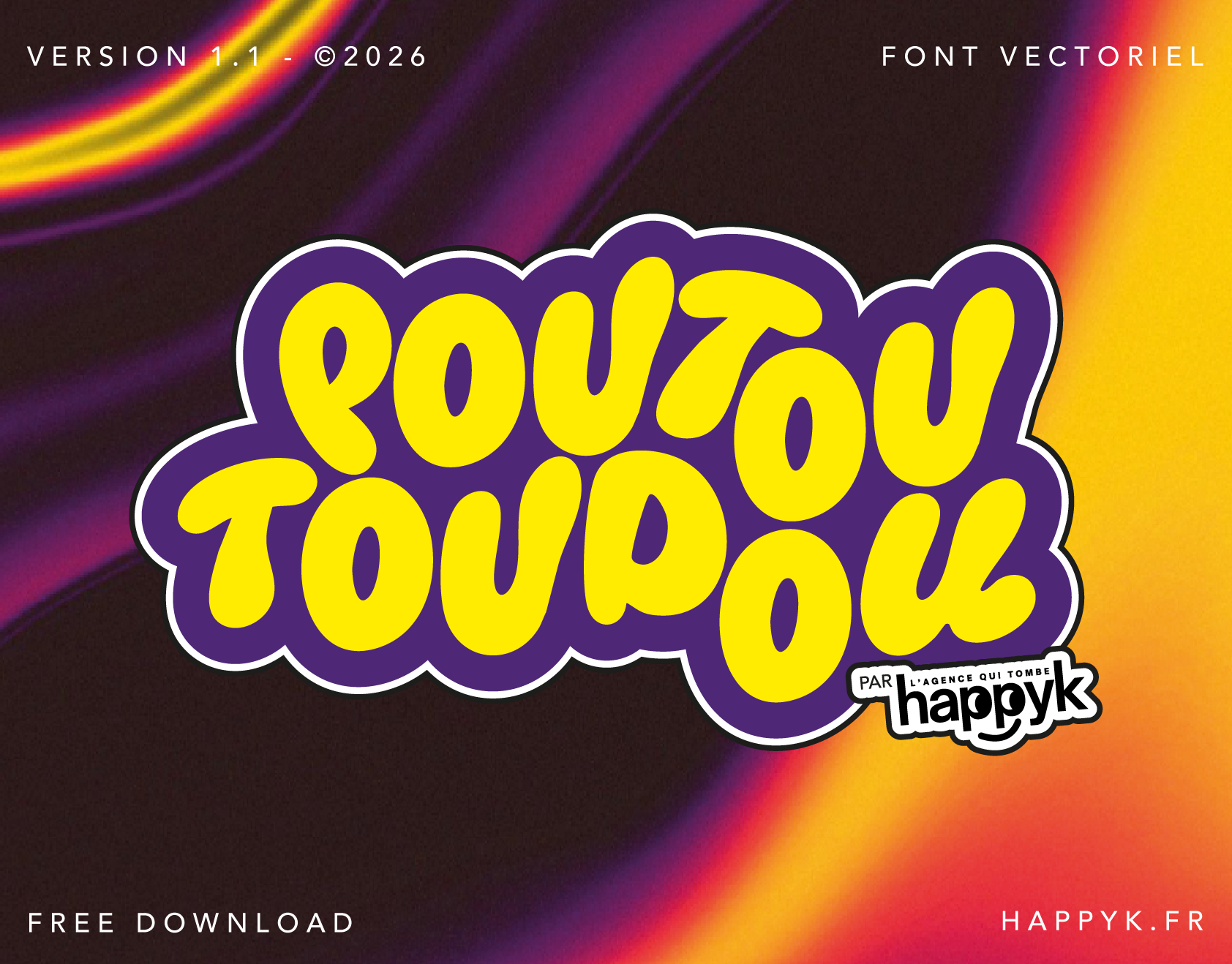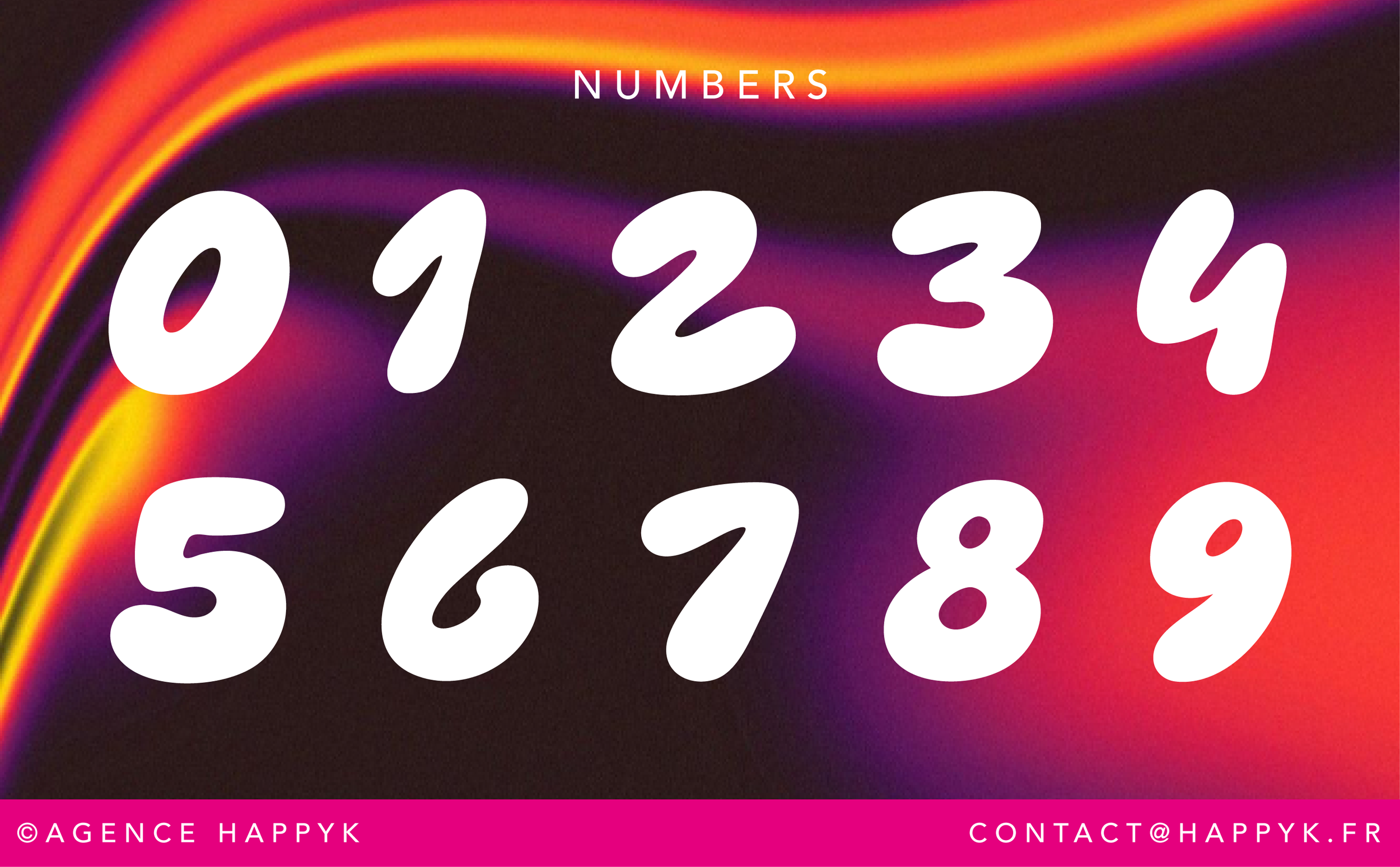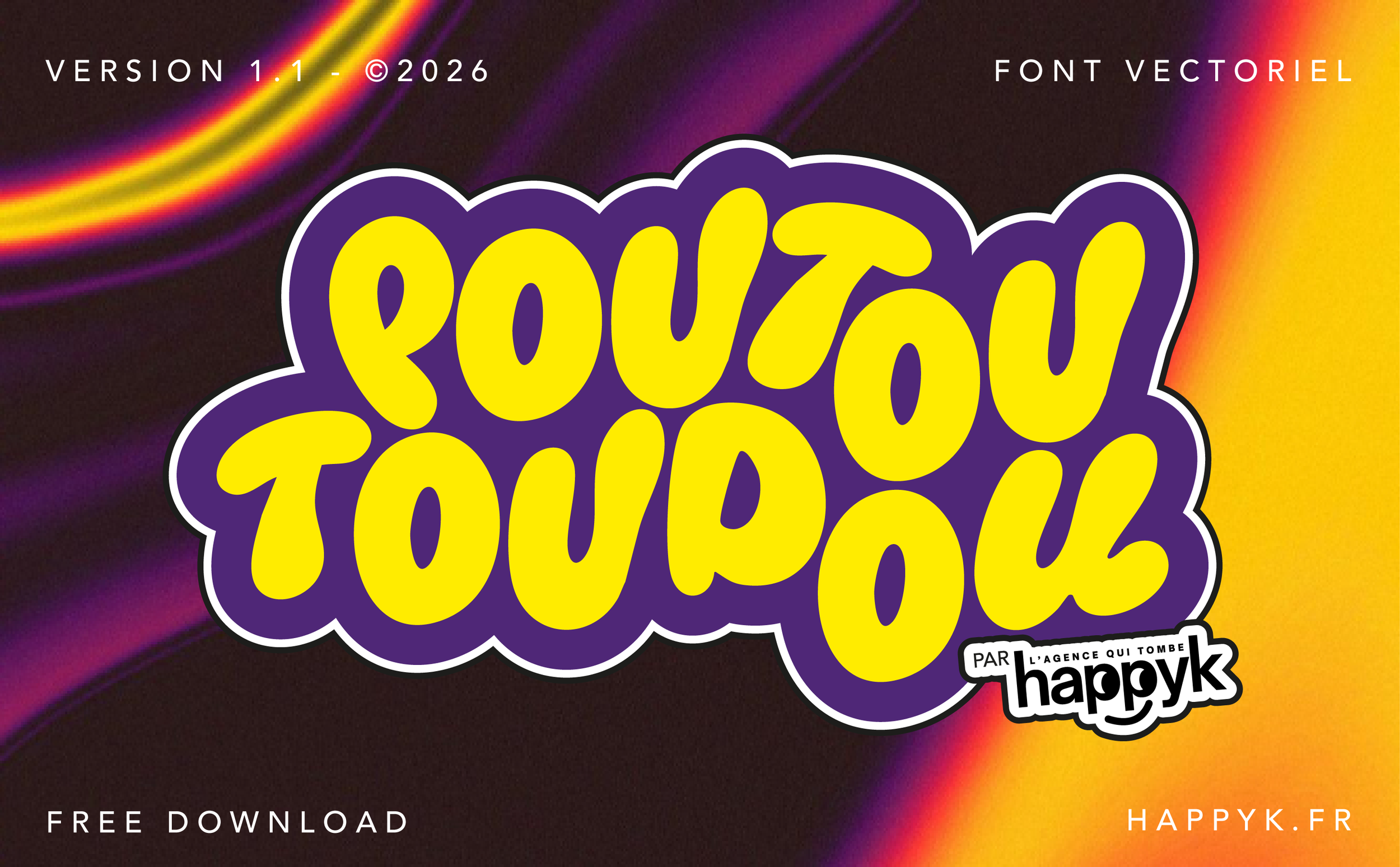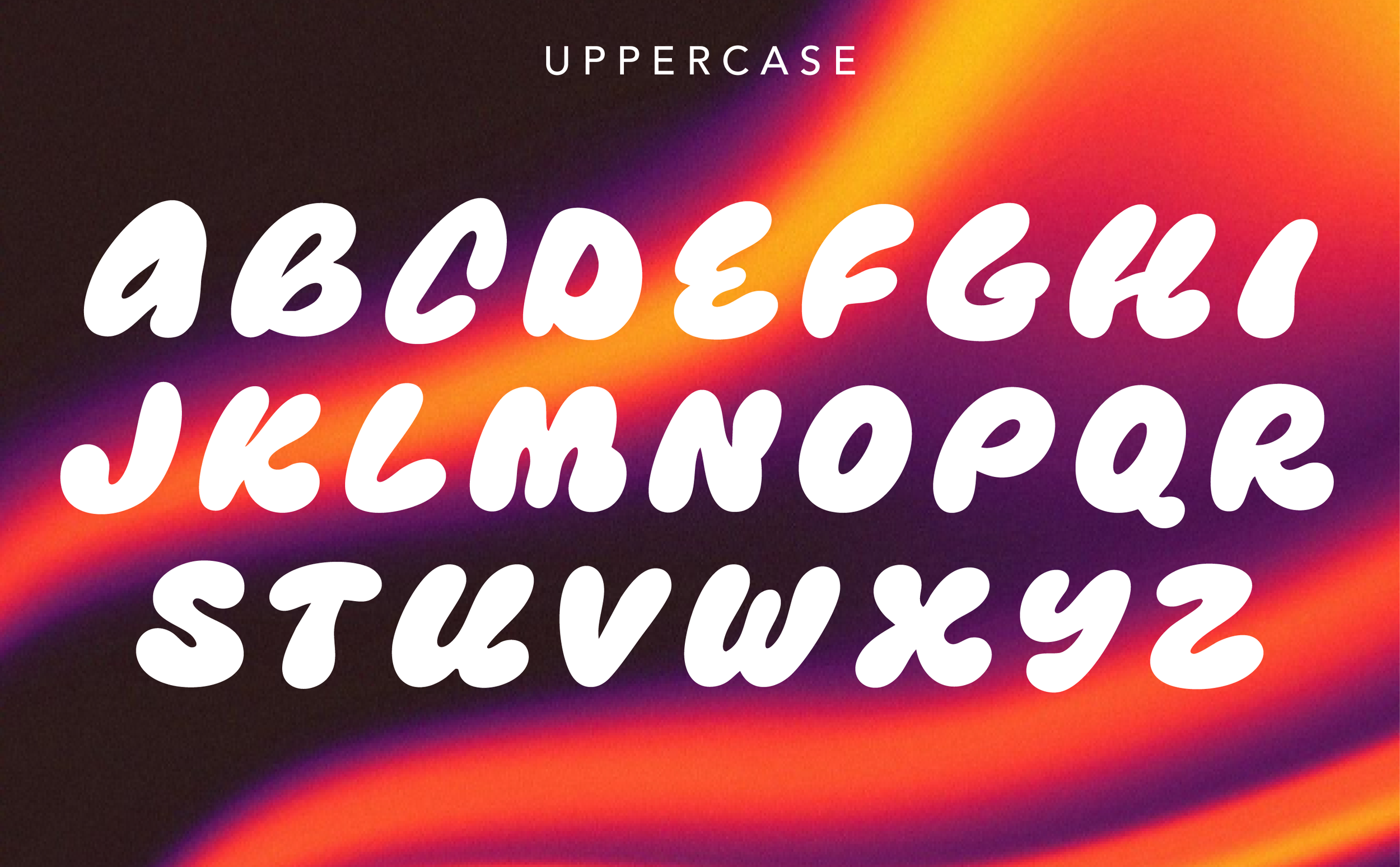
POUTOU TOUDOU
POUTOU TOUPOU
La police qui fait pto-pto-pto.
Poutou Toupou est une typographie ronde, généreuse et pleine d’énergie. Avec ses formes rebondies et son caractère assumé, elle apporte immédiatement une touche de bonne humeur à n’importe quel projet.
Parfaite pour les univers jeunesse, les packagings, les logos, les affiches ou les marques qui n’ont pas peur d’être joyeuses, colorées et un peu décalées.
Exubérante, fun et ultra lisible, elle est faite pour attirer l’œil et donner le sourire. 🍭✨